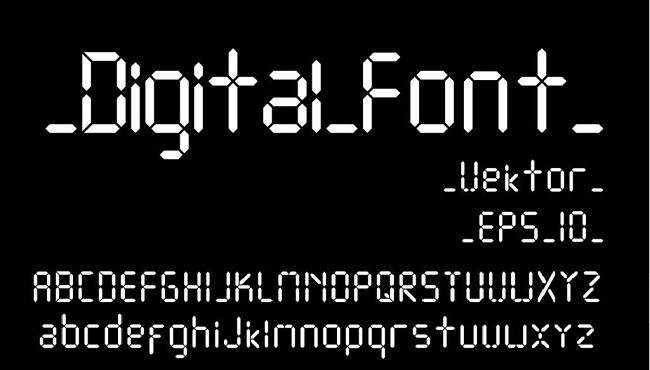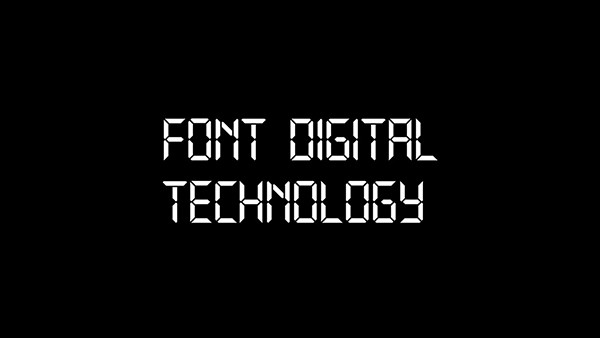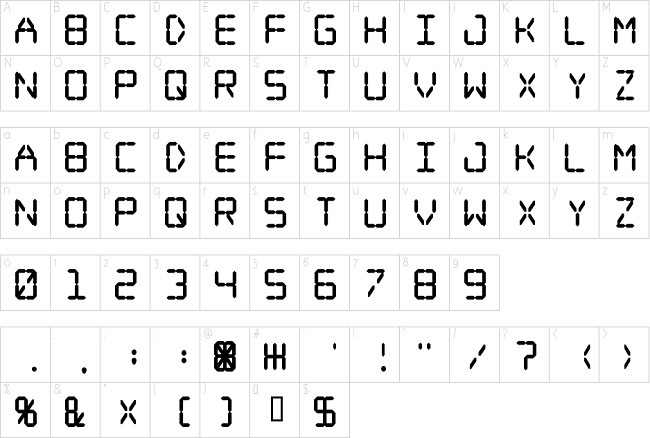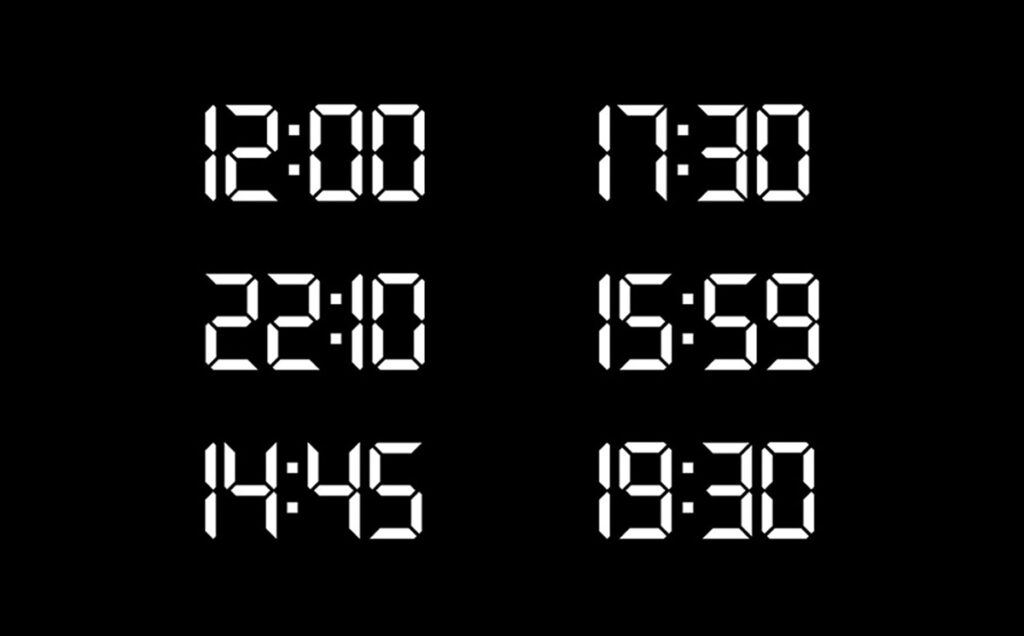
Font chữ đồng hồ điện tử (Digital 7-Segment Font) là nhóm phông chữ kỹ thuật mô phỏng cơ chế hiển thị của màn hình tinh thể lỏng và bóng LED 7 đoạn trên các thiết bị đo lường, đồng hồ điện tử hay bảng đếm ngược thời gian. Với tạo hình các thanh vát góc sắc sảo, tính đối xứng hình học cao và phong cách vị lai, phông chữ đồng hồ điện tử là chất liệu trực quan tuyệt vời để các kiến trúc sư, nhà thiết kế đưa cảm hứng công nghệ vào các bản vẽ phối cảnh bảng điều khiển Smart-home, phòng tập thể thao container hay hệ thống biển báo thông minh.
Cấu trúc ma trận 7 đoạn và phong cách công nghệ số của font chữ đồng hồ điện tử
Điểm cuốn hút của font chữ đồng hồ điện tử nằm ở nguyên lý cấu tạo từ 7 thanh phát quang riêng lẻ xếp theo hình chữ nhật đứng, tạo thành các con số và ký tự chữ cái với độ nghiêng nhẹ đặc trưng. Thay vì những đường cong mềm mại, phông chữ này sở hữu các đường cắt góc 45 độ dứt khoát, mang lại cảm giác chính xác, kỷ luật và cực kỳ nhạy bén với thông tin kỹ thuật số.
Sự ổn định về mặt thị giác của dòng font này tạo nên cảm giác hiện đại, đậm chất khoa học viễn tưởng và tính thực dụng cao. Khi kết hợp cùng các vật liệu kiến trúc thế hệ mới như vách kính đen phản quang, tấm tôn sóng container sơn màu xám khói, khung nhôm định hình hay hệ thống đèn LED ẩn trong các căn nhà lắp ghép thông minh, kiểu chữ này tạo nên sự tương thích thẩm mỹ đầy năng lượng.
Tư vấn từ chuyên viên: Font số đồng hồ điện tử sở hữu đặc thù thị giác dạng thanh ghép nối. Để bản thiết kế đạt hiệu quả thẩm mỹ tốt, bạn nên sử dụng phông chữ này cho các con số kỹ thuật, mốc thời gian hoặc các thông số đo lường (nhiệt độ, diện tích).
03 Ứng dụng phông chữ đồng hồ điện tử vào công trình thực tế
Nhờ vẻ ngoài giàu tính công nghệ và khả năng hiển thị thời gian nổi bật, bộ phông chữ này mang lại giá trị thực tế lớn trong khâu hoàn thiện các công trình hiện đại:
- Giao diện Bảng điều khiển Nhà thông minh: Những con số góc cạnh của font điện tử rất ăn ý khi lập trình hiển thị nhiệt độ, độ ẩm hay đồng hồ trên màn hình cảm ứng gắn tường nhà lắp ghép, tạo cảm giác tiện nghi và hiện đại cho chủ nhà.
- Hệ thống biển đếm ngược và Bảng bấm giờ Phòng Gym Container: Sử dụng font đồng hồ điện tử kết hợp đèn LED phát quang màu đỏ hoặc xanh lá giúp các hội viên dễ dàng theo dõi thời gian luyện tập từ mọi vị trí trong phòng tập.
- Bảng giá điện tử và Đồng hồ ngoài trời cho Trạm dịch vụ: Phông chữ này khi gia công trên hộp đèn LED hoặc biển alu khoét rãnh sẽ giúp các con số về giá xăng dầu, thông số trạm sạc hiển thị rõ nét cả ngày lẫn đêm.
03 Lưu ý bố cục font số đồng hồ điện tử luôn sắc sảo và dễ nhìn
Để khai thác hiệu quả vẻ đẹp của dòng font kỹ thuật số này mà không gây cảm giác đơn điệu cho bản vẽ, người thiết kế nên lưu tâm một số kinh nghiệm sau:
- Tạo hiệu ứng bóng mờ: Trong thiết kế giao diện đồ họa, bạn có thể nhân đôi layer chữ số, đặt lớp chữ bên dưới có màu xám mờ nhạt để mô phỏng chân thực các thanh LED 7 đoạn đang tắt, giúp thiết kế có chiều sâu thị giác hơn.
- Tránh sử dụng cho văn bản dài: Cấu trúc thanh gãy khúc của font số đồng hồ điện tử chỉ được thiết kế hoàn hảo cho các con số từ 0 đến 9 và một số chữ cái cơ bản. Việc dùng cho văn bản thông thường sẽ làm giảm đáng kể khả năng đọc hiểu.
- Lựa chọn màu sắc phát quang: Phông chữ phát huy hiệu quả thị giác cao khi phối cùng các tông màu LED kinh điển như xanh dương điện tử, xanh ngọc dạ quang, đỏ rực hoặc xanh lá trên nền đen tuyền, làm nổi bật đường nét sắc sảo của bộ chữ.